20个适合用作网页标题处英文字体演示及免费下载
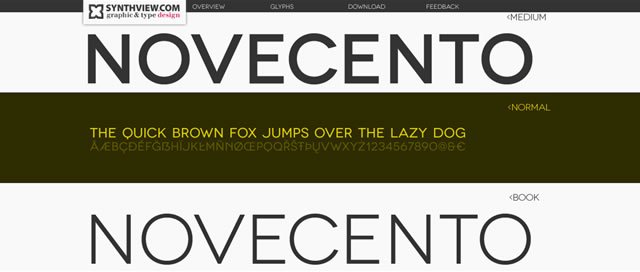
网页的header部分设计,可以说是网页整体设计中最重要的部分。而使用一个适合你自已网站风格的字体,又是重中之重。本文列举了20个适合网页头部使用的英文字体,简洁美丽大方。
Ostrich Sans (.ttf)
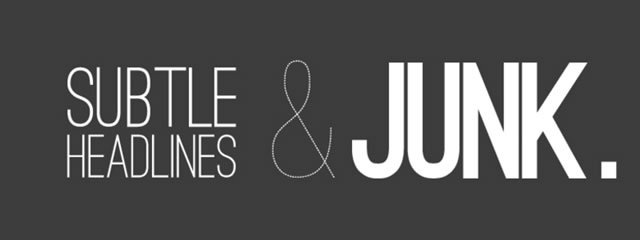
Novecento (.otf)
Sansus Webissimo (.otf)
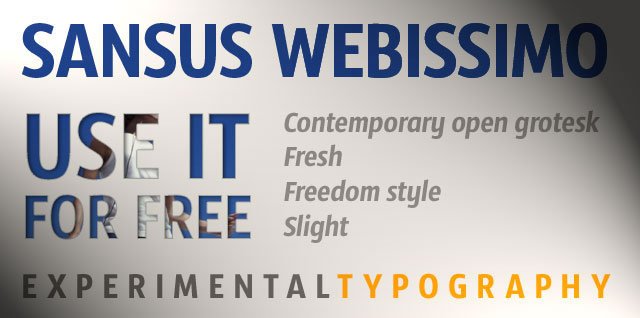
FF Sero Medium (.otf)
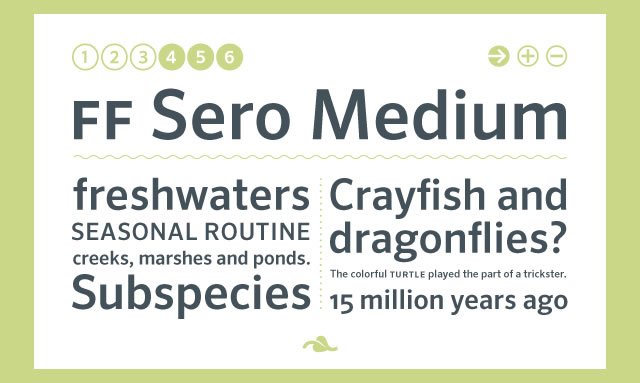
RBNo2 (.otf)
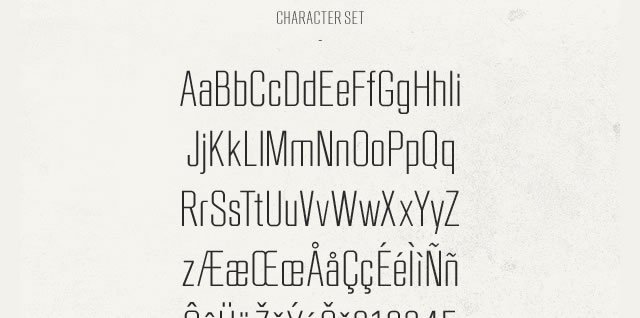
Governor (.ttf)
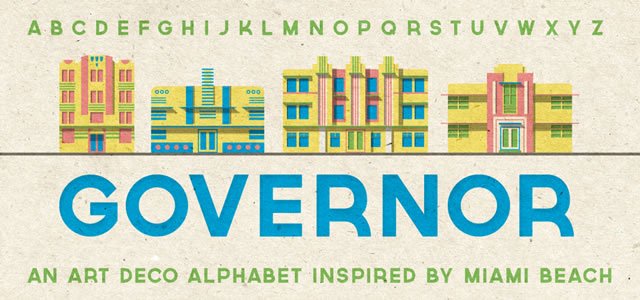
Sheep Sans (.ttf)
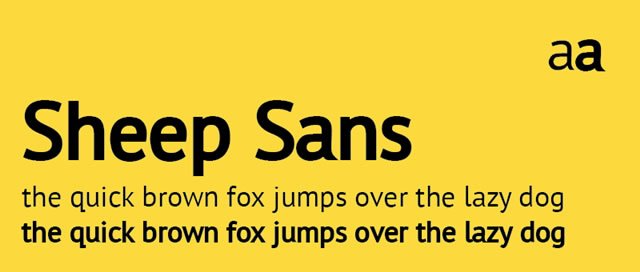
Carme Sans-Serif (.otf & .ttf)
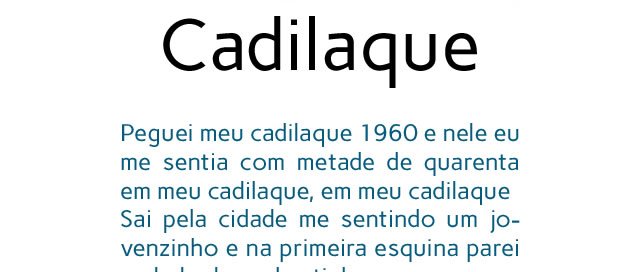
Muli (.ttf)
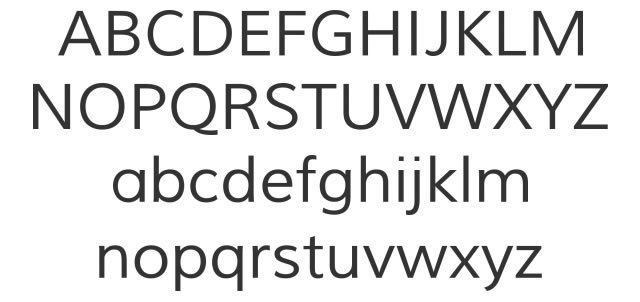
Infinity (.ttf)
Weston (.otf)
Quaver (.otf)
Tondu Beta (.otf)
Banda Regular (.otf)
Font FoglihtenFr02 (.otf)
Claire Hand Light & Reular (.otf)
Wisdom Script (.otf)
Legion Slab (.ttf)
and finally… SD Helveticons (.ttf)